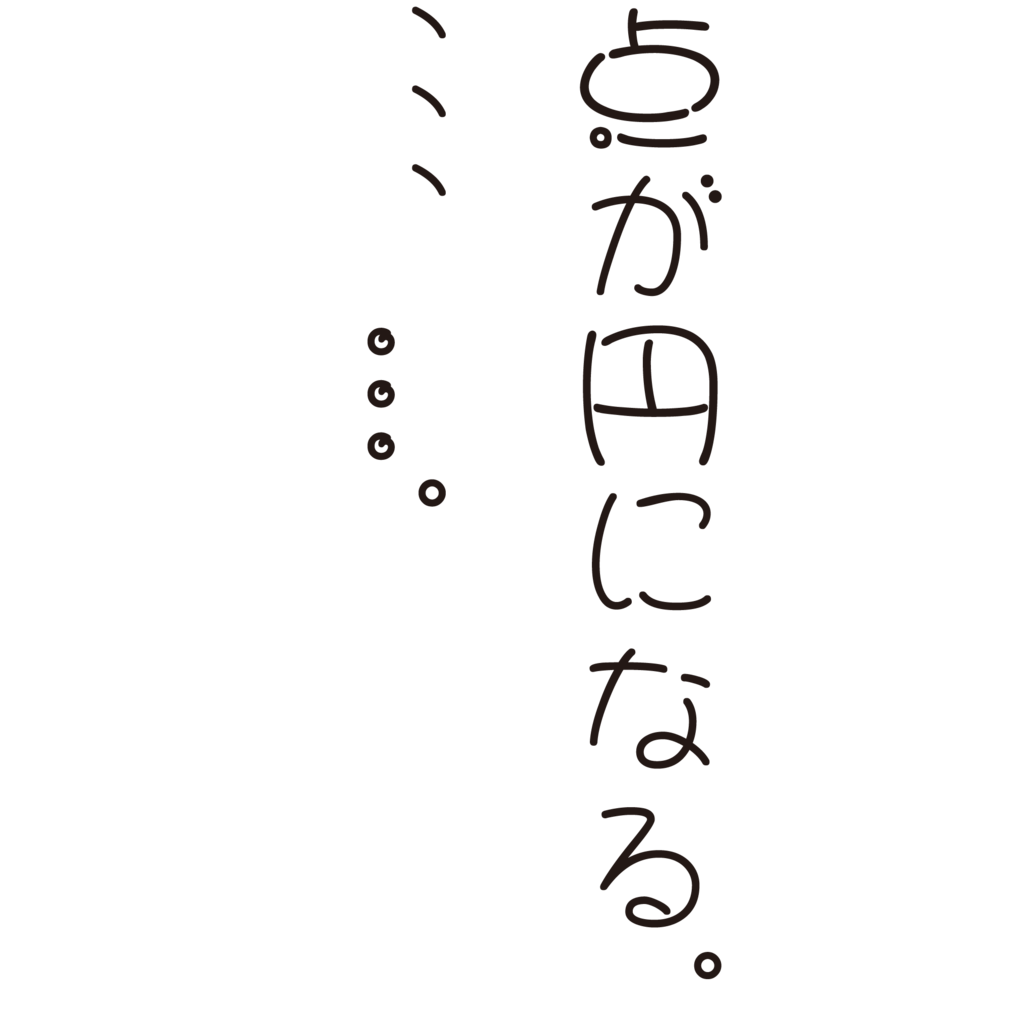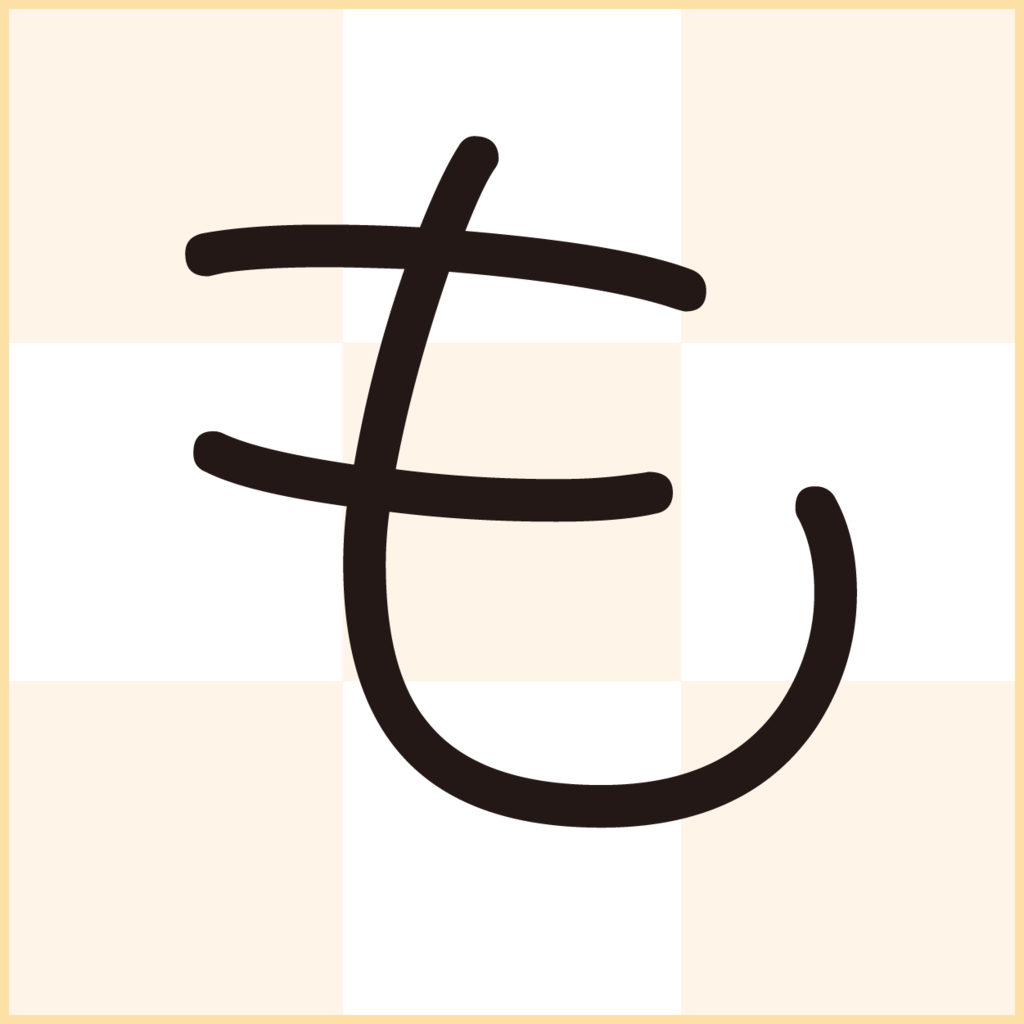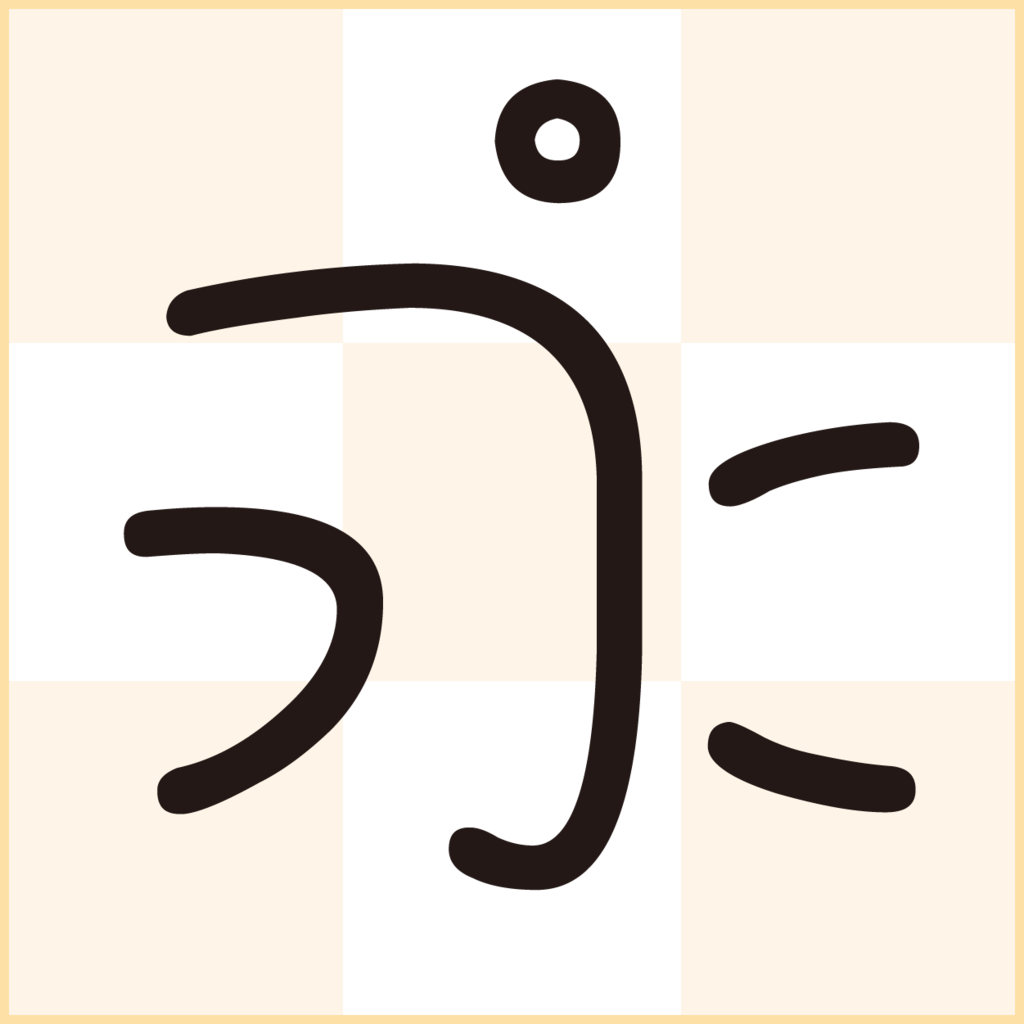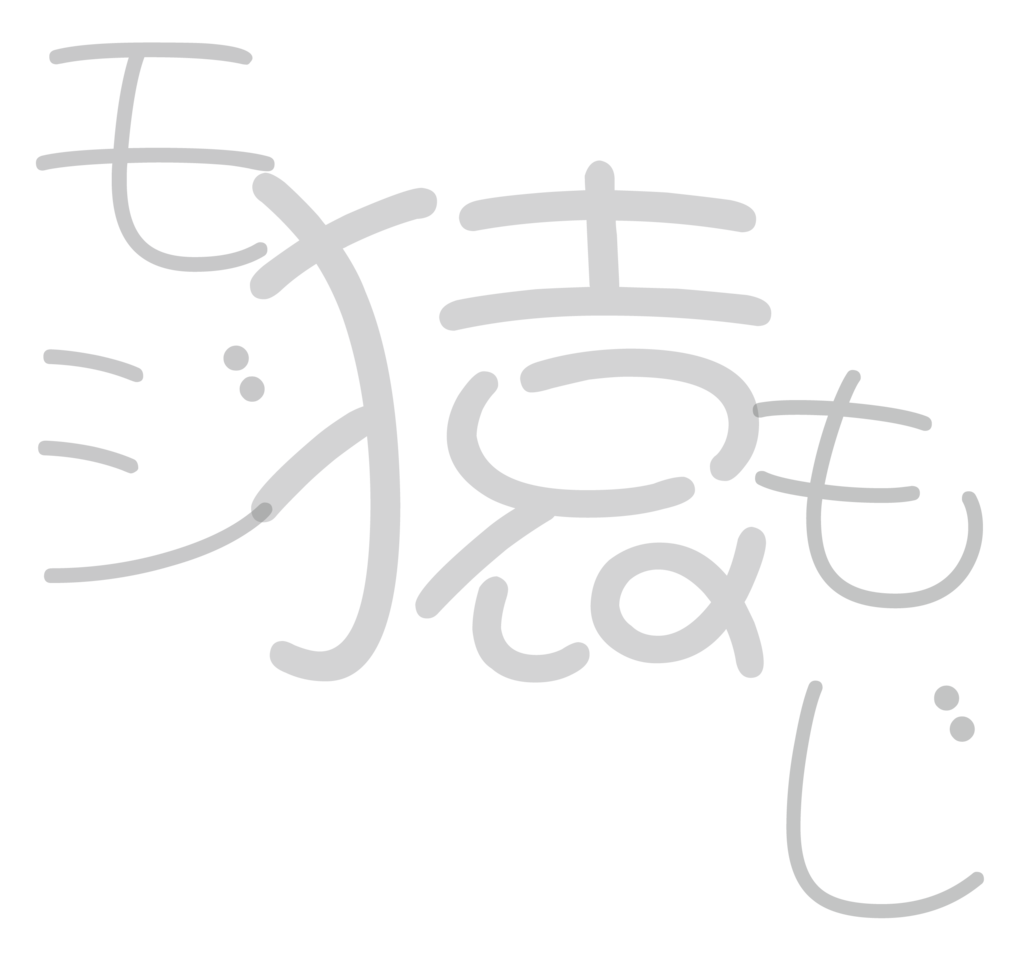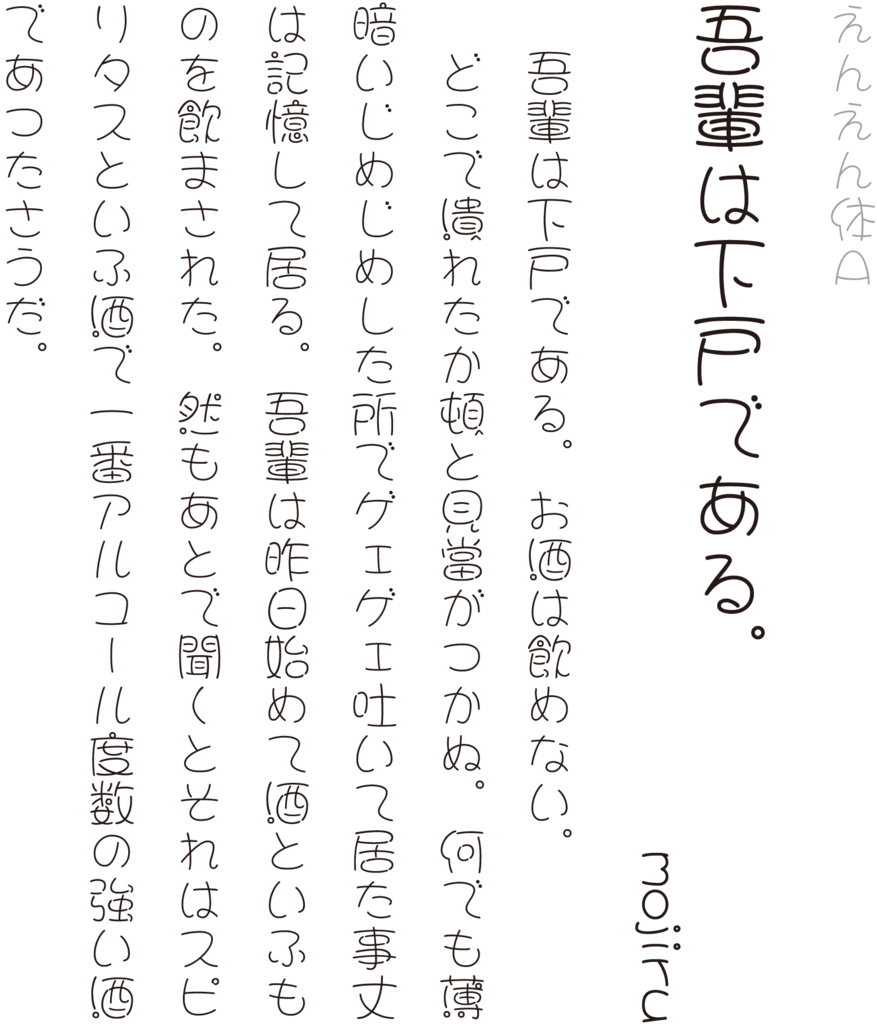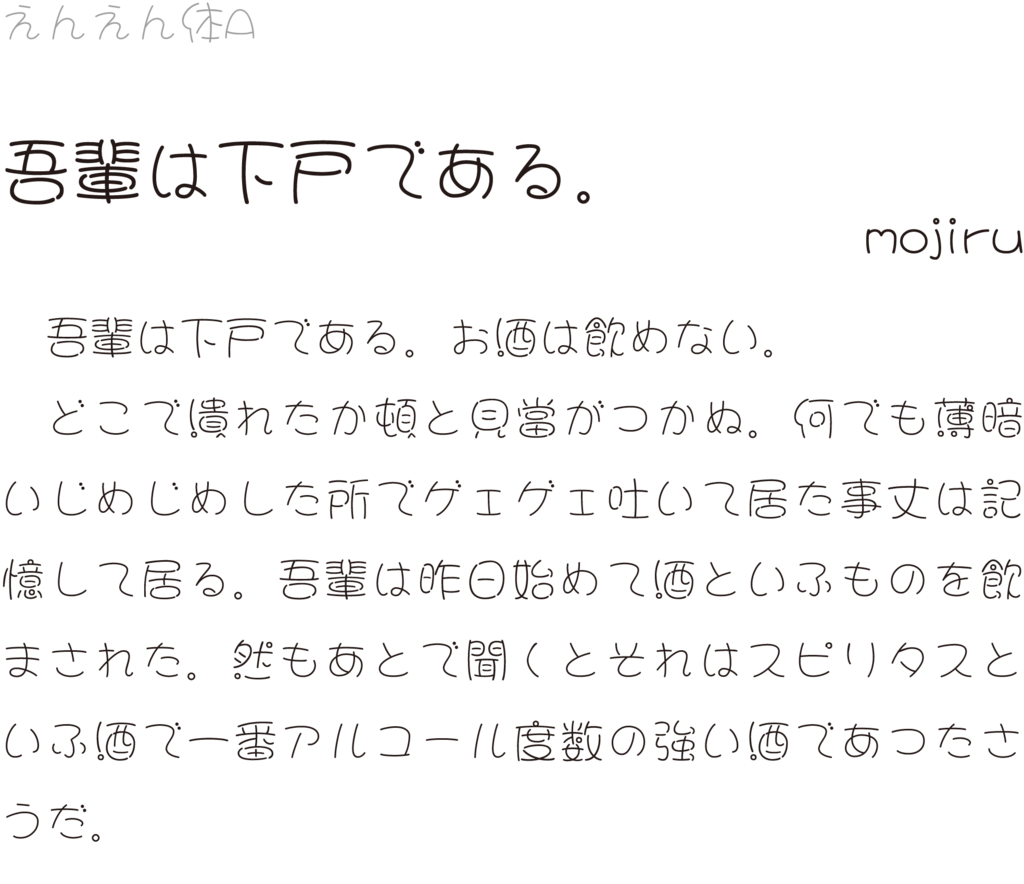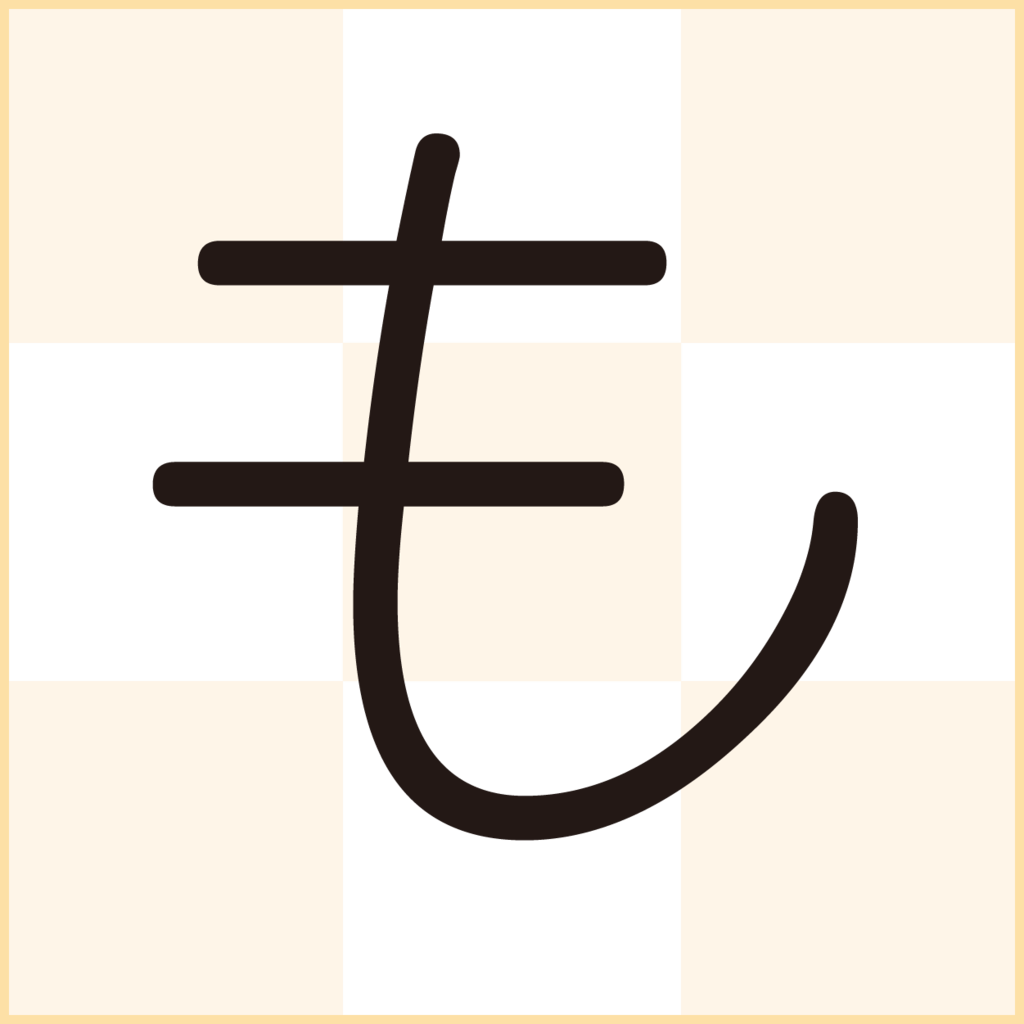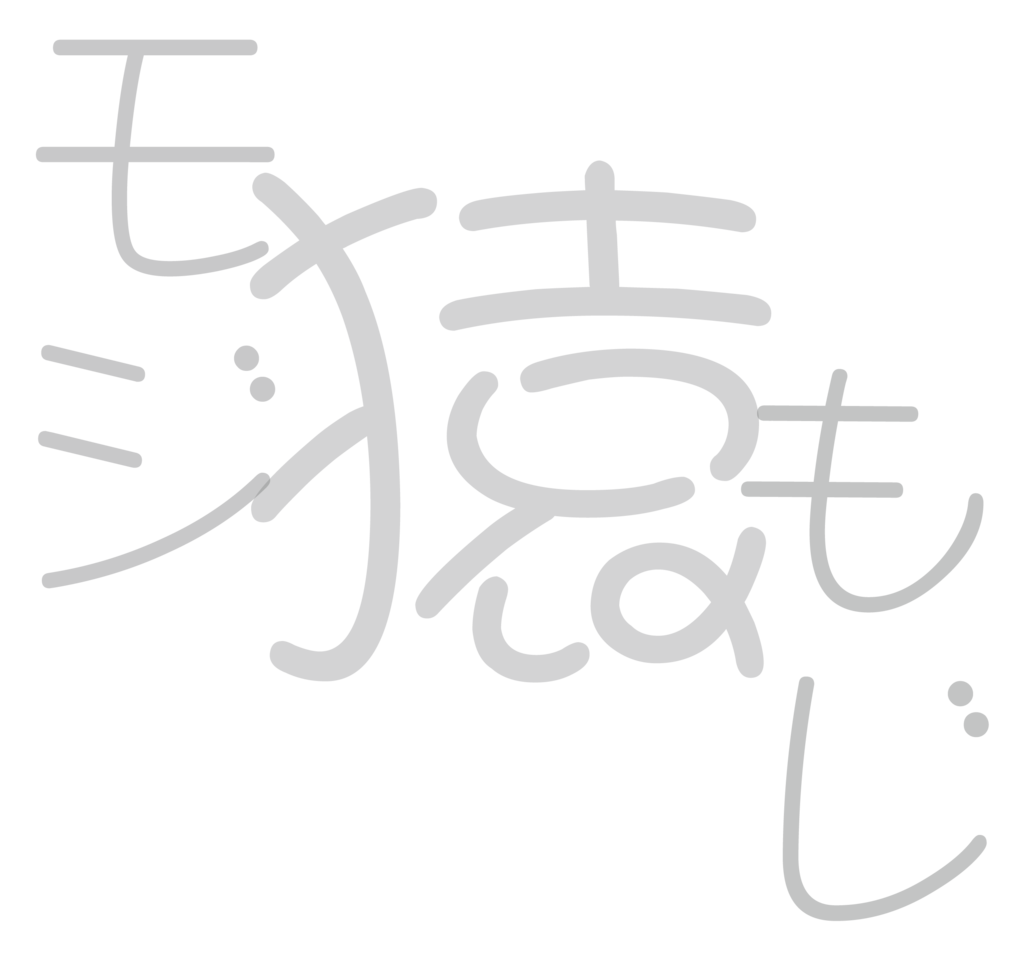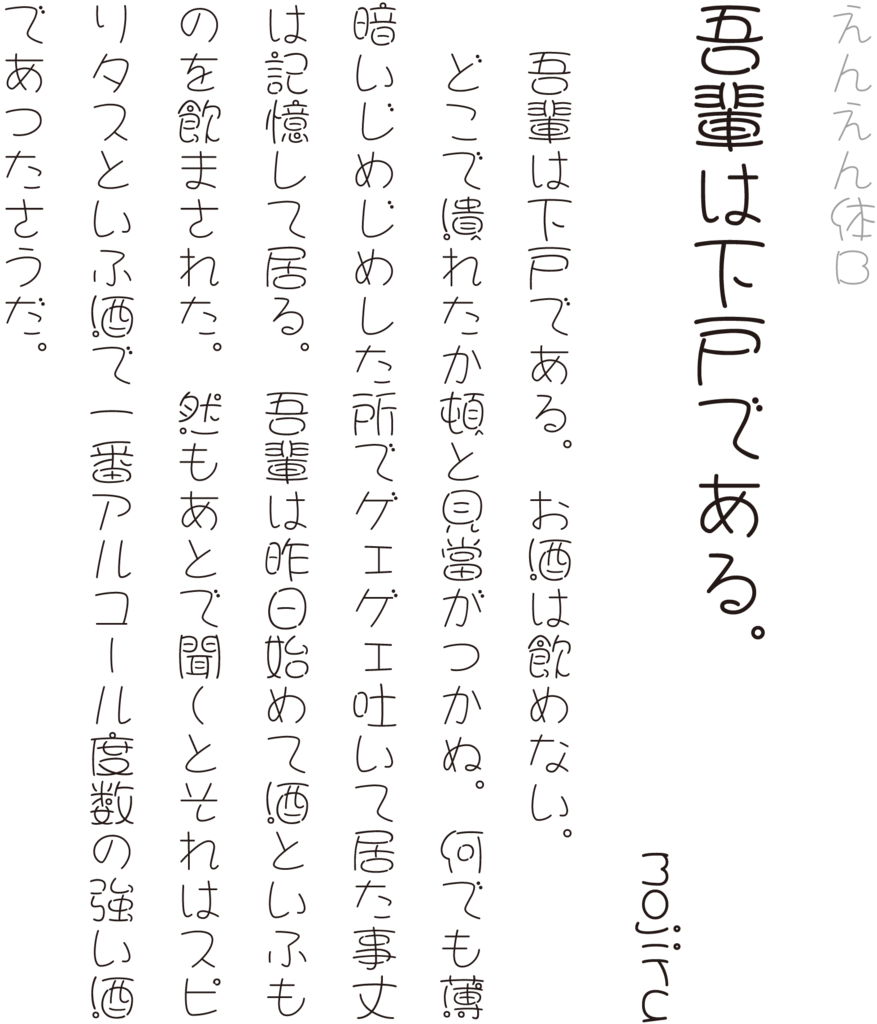
えんえん体
「えんえん体」は、ストロークの一部が円になっているデザイン書体。字形が丸く、円形のストロークに加えてバランス感のない構成が特徴。一部の点も円形にデザインされている。 えんえん体にはえんえん体Aとえんえん体Bがあり、平仮名・片仮名の字形が異なる。
えんえん体Aの書体見本
えんえん体Bの書体見本